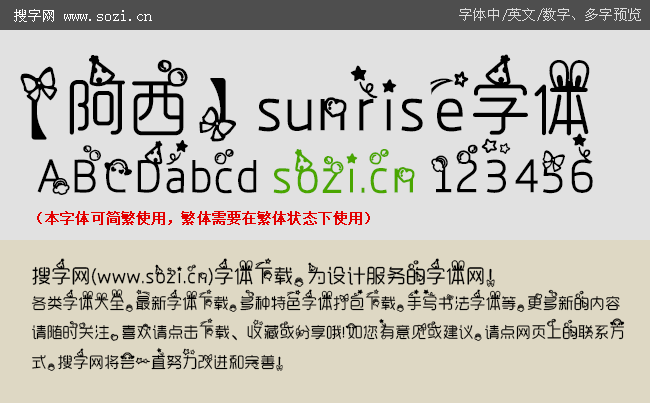
sunrise字體
搜字網(wǎng)給大家提供一款很有趣的手機(jī)中文字體下載。字體名字叫sunrise字體,這款手機(jī)字體是在造字工房悅黑體字體筆畫間插入了大量可愛的卡通圖案。趣味性實(shí)足,又保持了文字的識(shí)別度,特別適合喜歡手機(jī)字體個(gè)性一些的朋友在手機(jī)上安裝使用。